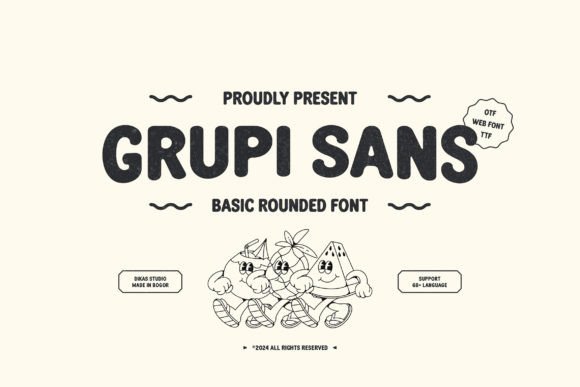
Grupi Sans
Grupi Sansのような高品質の素材をお探しの場合、このプレミアムパッケージはクリエイティブなプロジェクトに素晴らしい選択です。
精密に作られたGrupi Sansは、クリーンなベクター、滑らかなタイポグラフィ、そして安心のための商用ライセンスを提供します。
POD(オンデマンド印刷)製品、結婚式の招待状、またはソーシャルメディアのグラフィックを作成している場合でも、Grupi Sansは理想的です。